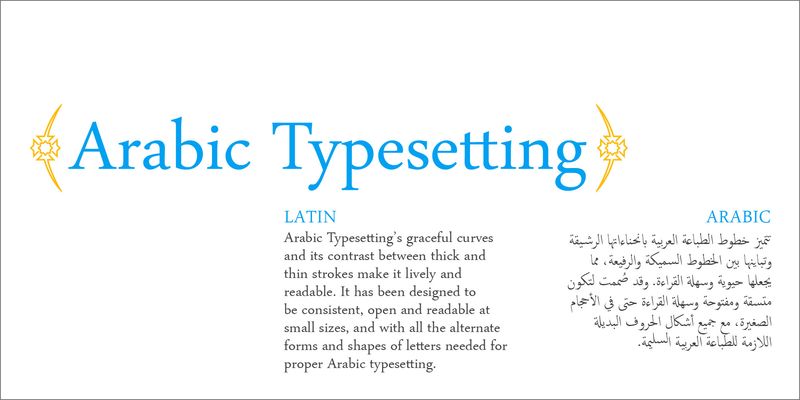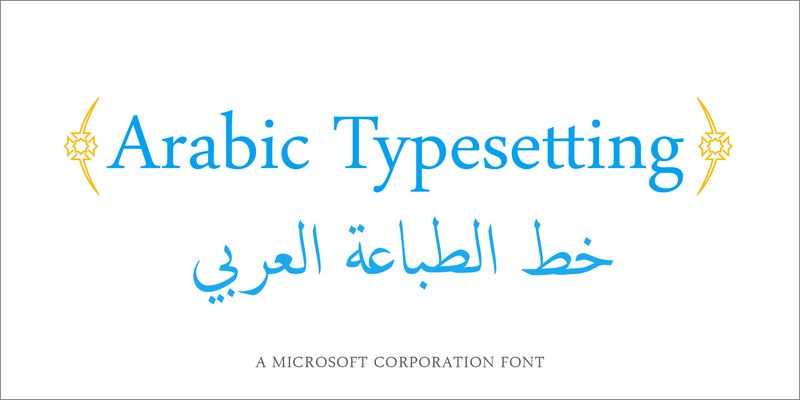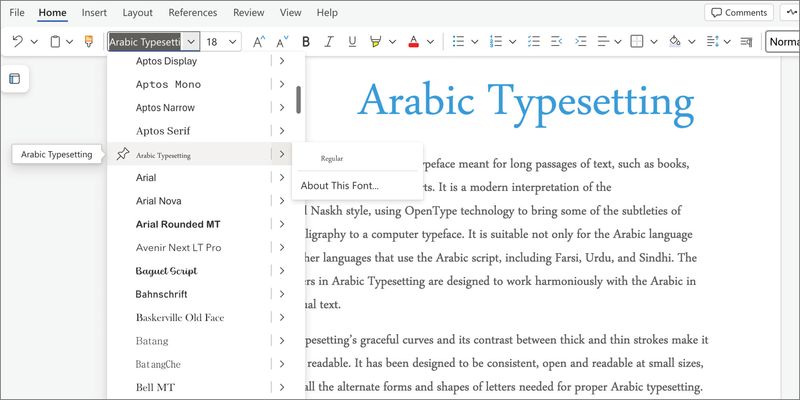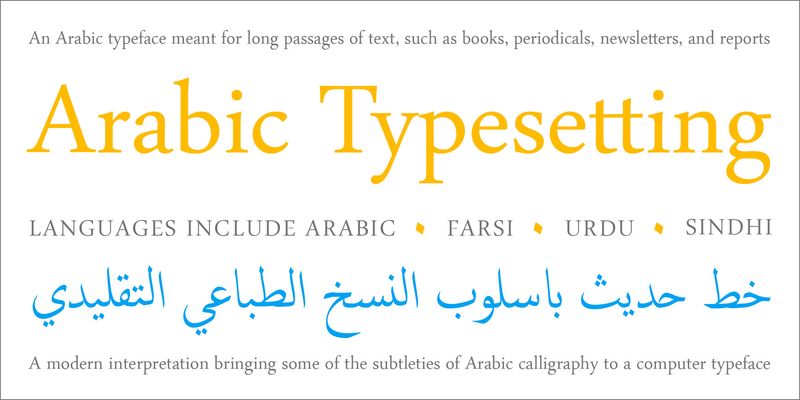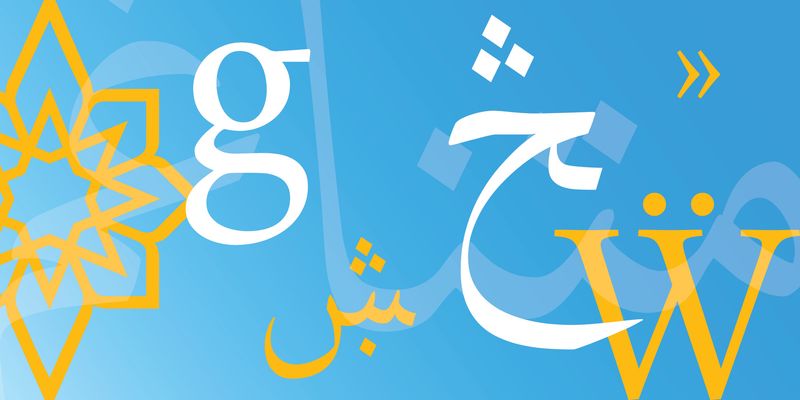
Arabic Typesetting は、書籍、定期刊行物、ニュースレター、レポートなどの長い本文用のアラビア語の書体です。伝統的なナスフ体を現代的にしたもので、OpenType 技術を使用して、アラビア文字の繊細さの一部をコンピューターの書体にも取り入れています。アラビア語だけでなく、ペルシャ語、ウルドゥー語、シンド語など、アラビア文字を使用する他の言語にも適しています。Arabic Typesetting のアルファベットは、多言語が含まれたテキストでアラビア語と調和するようにデザインされています。
Arabic Typesetting の優美な曲線や太い線と細い線のコントラストにより、生き生きとした読みやすい書体になっています。小さなフォントサイズでも一貫性があり、オープンで読みやすいようにデザインされており、アラビア文字を適切に組むのに必要な代替文字と形状をすべて備えています。
書体デザイナーの Mamoun Sakkal、Paul C. Nelson、John Hudson が共同で、Microsoft のアラビア語書体のデザインに取り組みました。